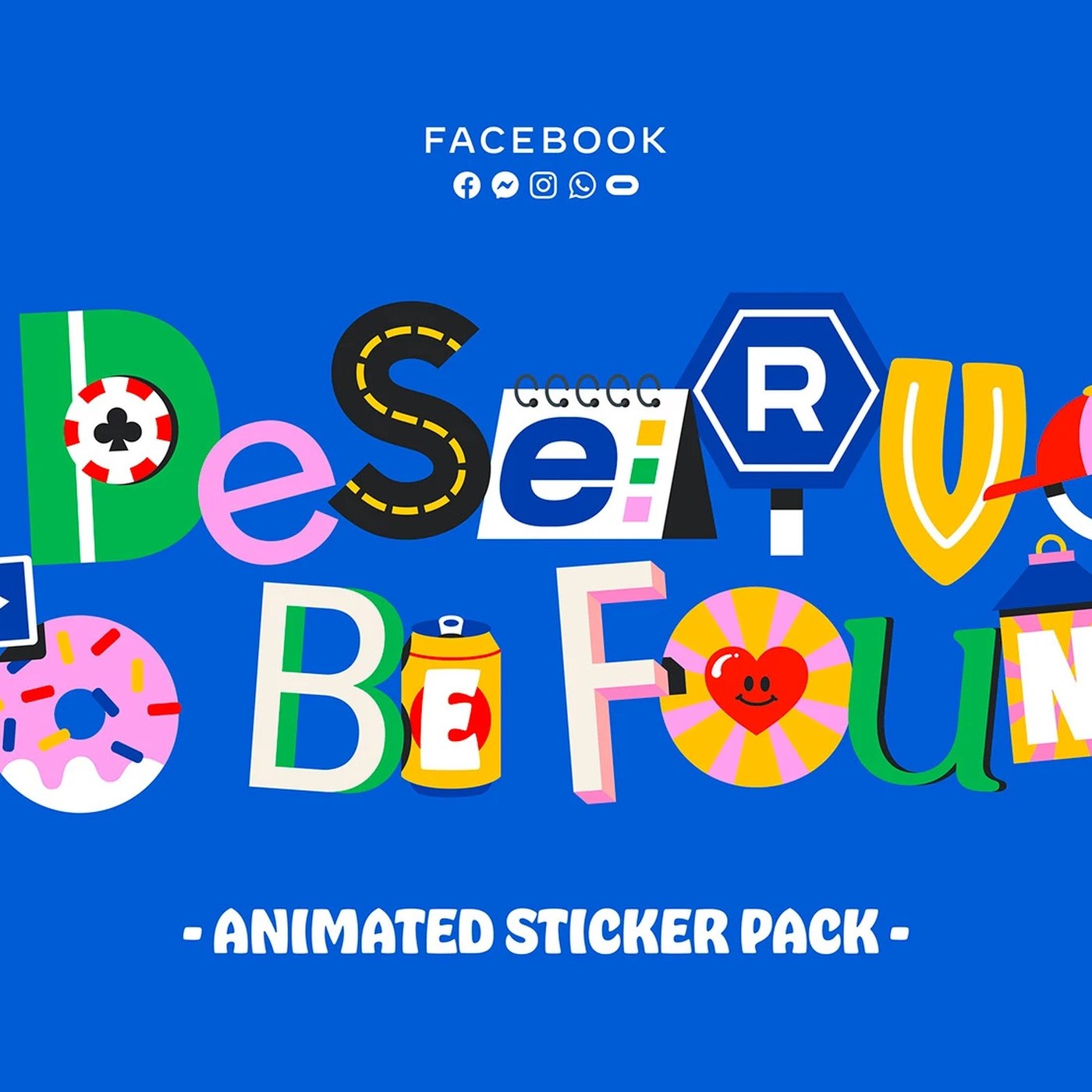
Pegatinas animadas de tipografía dinámica: tablero de Facebook de Mat Voyce
Los stickers animados de tipografía dinámica representan la transformación dinámica de los materiales de eventos digitales. Facebook encargó al diseñador de movimiento Mat Voyce la creación de la campaña. Creó veinte bucles personalizados para pequeñas empresas. Estos recursos impresos captan la atención de flujos de noticias abarrotados a través de movimientos divertidos. Este proyecto redefine la publicidad comercial local transformando texto promocional en personajes animados.
Cada ciclo está compuesto íntegramente por letras ilustradas. Los personajes rebotan, giran y se estiran. Esta expresión introduce una fuerte tensión compositiva en una simple llamada a la acción. En lugar de una fuente corporativa estándar, Voyce utilizó restricciones geométricas para mantener una legibilidad absoluta. El ritmo visual de cada palabra se mantiene regular. La física de movimiento suave mejora la personalidad audaz de la fuente personalizada. Los diseñadores pueden analizar este equilibrio entre la energía cinética y las reglas de diseño estructural.
Diseñar pegatinas animadas de tipografía dinámica.
Las letras personalizadas retroceden o se expanden dentro de una estrecha cuadrícula modular. Esta estructura equilibra el espacio negativo y las pinceladas gruesas y hechas a mano. Cada diseño presenta un alto contraste táctil, evocando una sensación física en la pantalla plana de vidrio. Las letras funcionan como personajes animados activos en lugar de información estática. Al manipular la alineación de la línea base, Vois se aseguró de que cada pegatina funcionara como un diseño independiente. crear estos Pegatinas animadas de tipografía dinámica. Requiere una sólida comprensión de la sincronización y la animación vectorial. La jerarquía resultante guía la mirada del espectador a través de la composición en movimiento.
El diseño nostálgico y basado en personajes continúa dando forma a las campañas contemporáneas en las redes sociales. El trabajo de Voyce hace referencia a tipos de letra de dibujos animados medievales mientras utiliza herramientas vectoriales modernas. Demuestra la utilidad de los activos de marca personalizados para los comerciantes locales. El proyecto destaca la creciente demanda industrial de estos productos Pegatinas animadas de tipografía dinámica.. Los diseñadores deben estudiar cómo estos activos mantienen el impacto visual en el tamaño más pequeño de los dispositivos móviles.